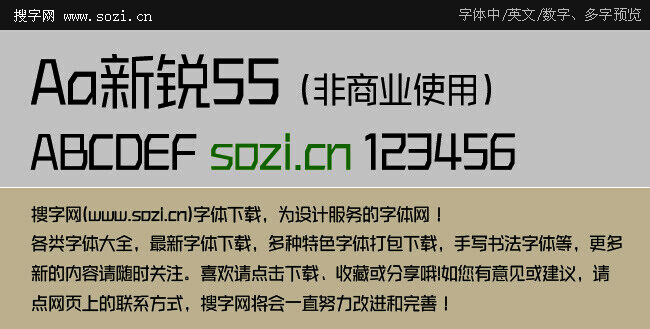
Aa新銳55
搜字網(wǎng)給大家提供一款A(yù)a新銳55(非商業(yè)使用)中文字體下載,該字體是一款中文藝術(shù)字體,字體共有七個(gè)字重,字體風(fēng)格簡潔大方,筆畫銳利新潮,散發(fā)一種青春的活力。適合圖書設(shè)計(jì)、包裝設(shè)計(jì)、海報(bào)設(shè)計(jì)等應(yīng)用(此字體為個(gè)人非商用版,商用可以聯(lián)系QQ:1006760504)。